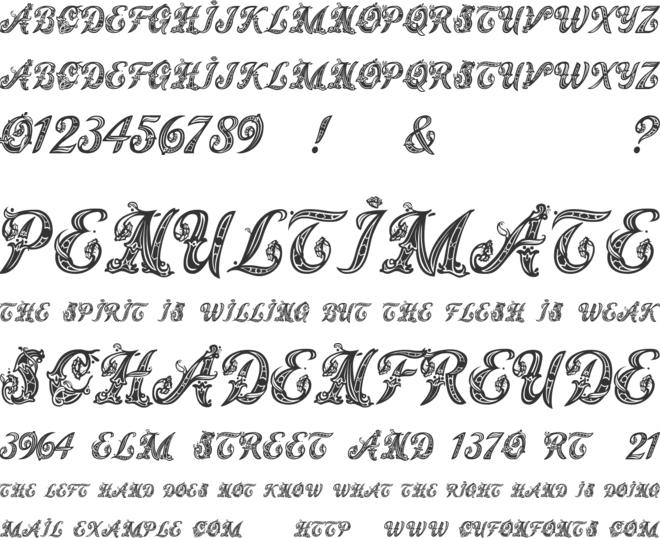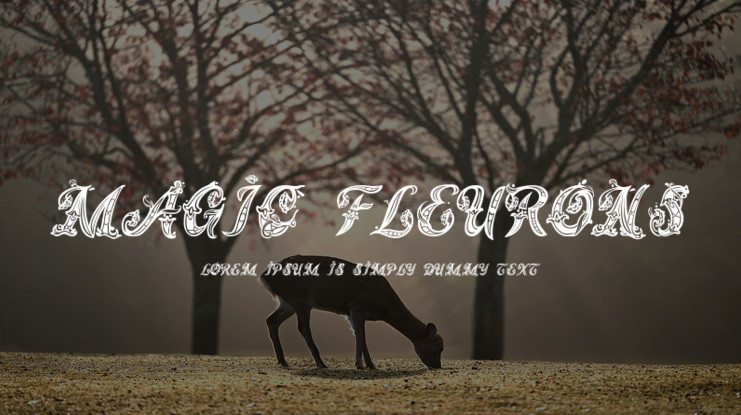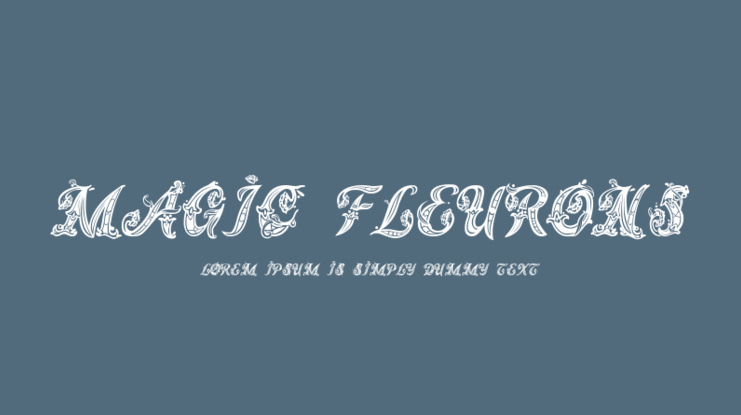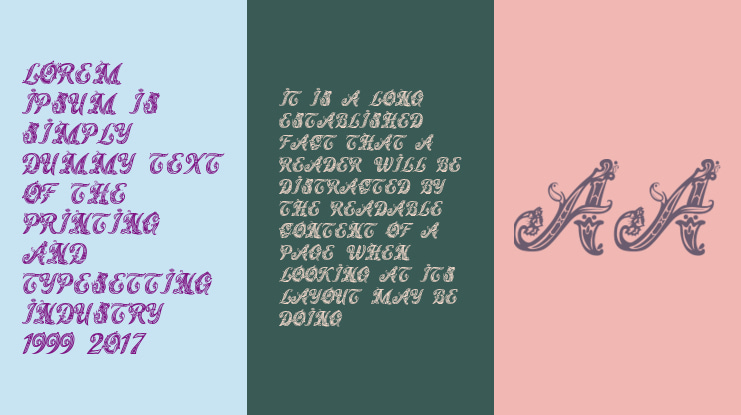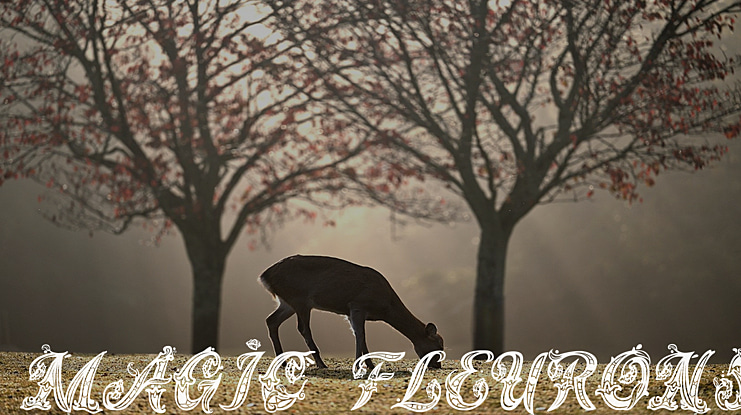
Magic Fleurons Font
Esta fuente solo funciona si tienes activadas las mayúsculas. Funcionan perfecto para capitulares aunque como opción pueden usarse para display u ornamentación de páginas.